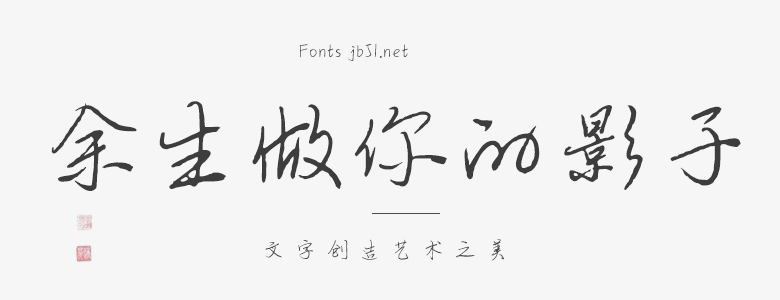
"余生做你的影子"是一款獨(dú)特且富有情感的字體。設(shè)計(jì)這款字體時(shí),我致力于創(chuàng)造出一種能夠準(zhǔn)確傳達(dá)其名字中蘊(yùn)含的溫情和深情的視覺語言。 這款字體的基本形狀來源于“影子”的意象,橫細(xì)豎粗,帶有一種朦朧的美感。每一個(gè)字母都仿佛在紙面上留下了深深的影子,如同人生的印記,清晰而深刻。特別值得一提的是,字體的“豎”筆畫末端呈現(xiàn)出獨(dú)特的弧形,如同一個(gè)人在陽光下留下的影子,充滿了生動(dòng)和活力。 “余生做你的影子”的字體風(fēng)格既有一種粗獷的力度,又有一種溫柔的細(xì)膩,二者完美地結(jié)合在一起,形成了獨(dú)特的視覺沖擊力。同時(shí),字體的嚴(yán)謹(jǐn)和規(guī)范也體現(xiàn)了對(duì)細(xì)節(jié)的極度關(guān)注和對(duì)工作的熱情。 總的來說,這款字體不僅僅是一種視覺表達(dá),更是一種情感的傳遞。它表達(dá)了我們對(duì)愛情的深深承諾,以及在我們的人生旅途中,我們希望成為彼此的支持和力量的愿望。這是一種富有感情和溫度的字體,適合用于各種需要表達(dá)深情和溫情的場(chǎng)合。